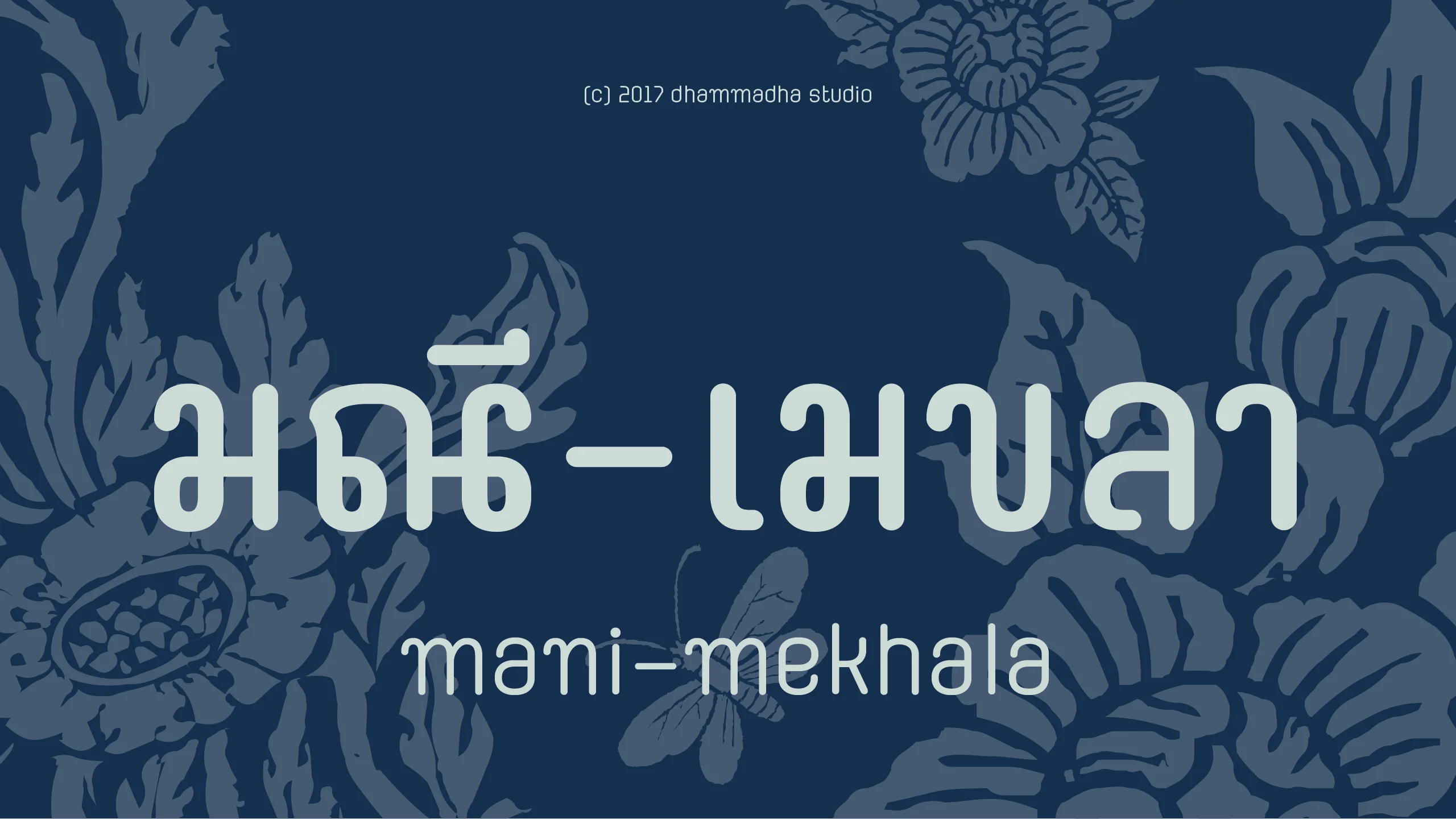
mani-mekhala
"มณี-เมขลา | mani-mekhala" คือชุดอักษรที่ผ่านการคิดค้นและจัดระบบมาอย่างละเอียดเพื่อส่งมอบประสบการณ์การใช้งานที่ดีที่สุด โดยเริ่มต้นจากความตั้งใจที่จะรวบรวมความหลากหลายของตัวอักษรไว้ในชุดเดียว แต่เพื่อแก้ปัญหาความซับซ้อนในการเรียกใช้ชุดอักษรสำรองในโปรแกรมต่างๆ เราจึงตัดสินใจแยกชุดอักษรนี้ออกมาเป็นสองรูปแบบคือ 'มณี' และ 'เมขลา' เพื่อให้ดีไซน์เนอร์สามารถเลือกใช้และสลับสไตล์ได้อย่างสะดวกสบาย มั่นใจได้ในความสมบูรณ์แบบของการแสดงผลในทุกซอฟต์แวร์และทุกการทำงาน ด้วยโครงสร้างตัวอักษรที่เน้นความประณีตและการจัดวางที่ลงตัว "มณี-เมขลา | mani-mekhala" จึงเป็นตัวเลือกที่ช่วยเสริมความโดดเด่นให้กับงานออกแบบที่ต้องการความแตกต่างแต่ยังคงความเป็นมืออาชีพ ไม่ว่าจะเป็นการนำไปใช้ในงานอัตลักษณ์แบรนด์ งานจัดหน้าสิ่งพิมพ์ หรือสื่อดิจิทัลที่ต้องการความสม่ำเสมอในการสื่อสาร การแยกชุดอักษรนี้ไม่เพียงแต่ช่วยให้การทำงานง่ายขึ้น แต่ยังช่วยเปิดพื้นที่การสร้างสรรค์ให้คุณเลือกผสมผสานเสน่ห์ของทั้งสองรูปแบบเข้าด้วยกันได้อย่างไร้ข้อจำกัด